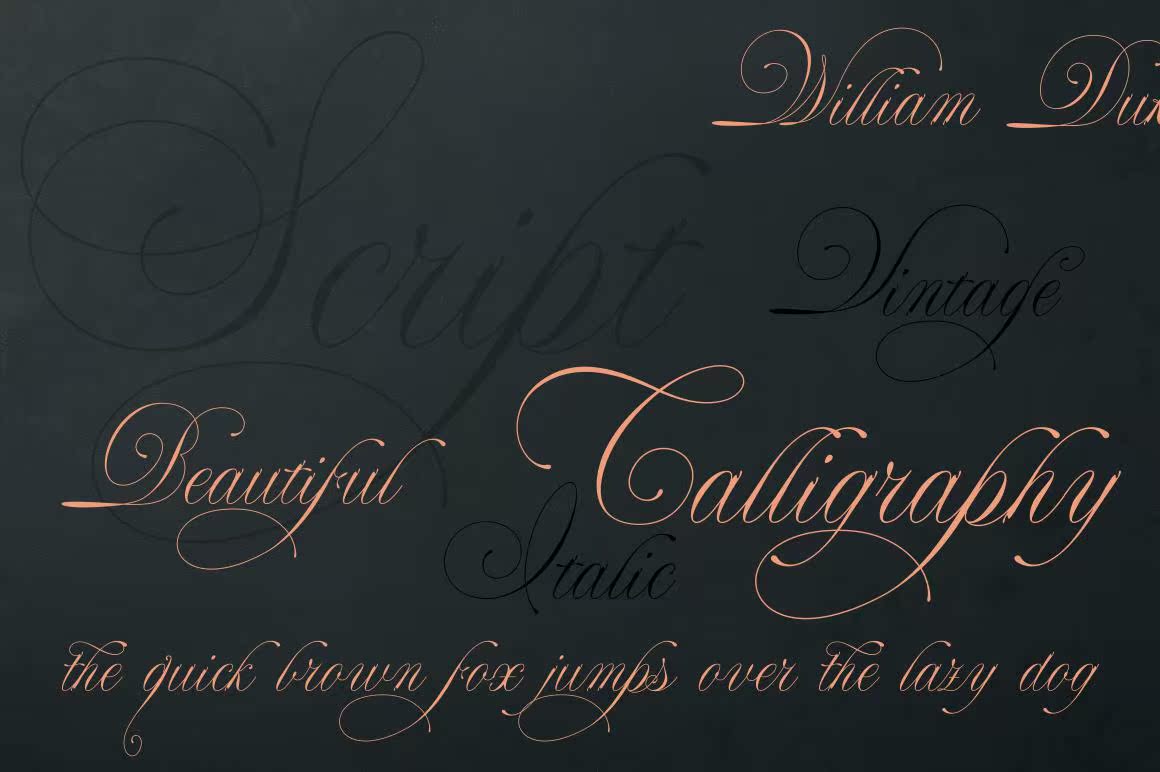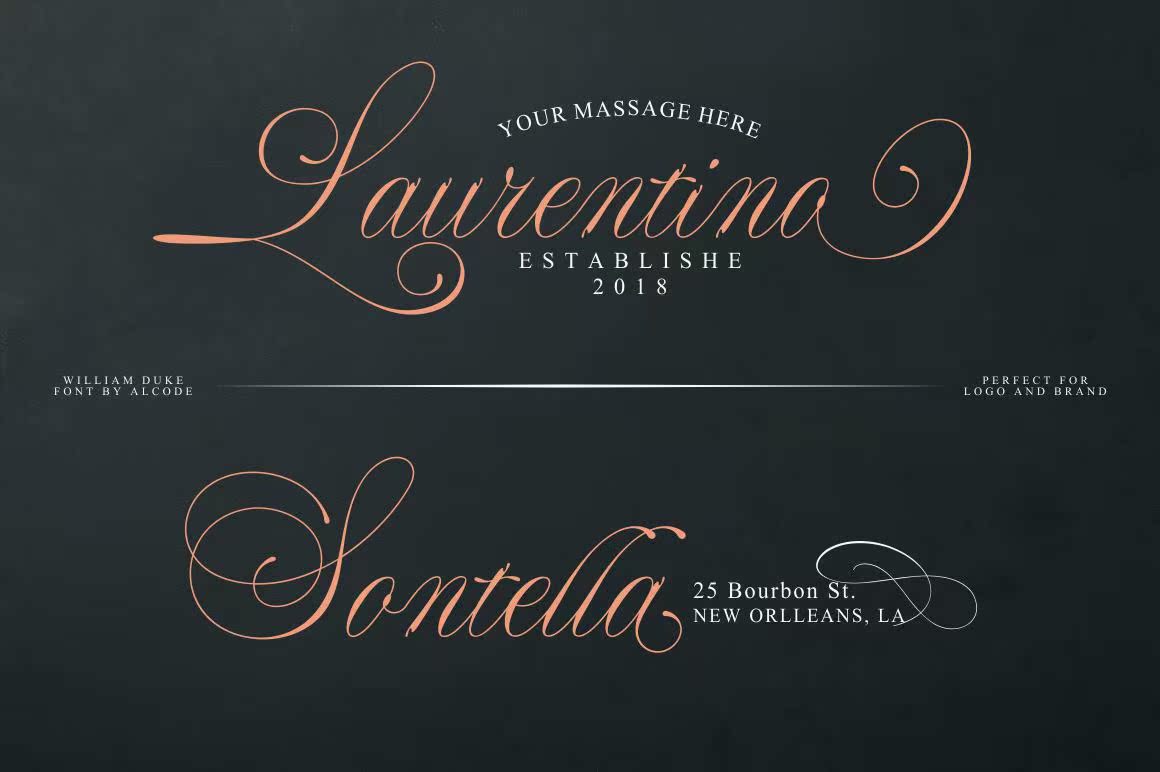
WiliamDukeisaclassicfont.具有开放式打印功能,它可以消除19世纪英国人的手写感觉。因此,它非常适合于婚礼媒体、书皮、贺卡、徽标、品牌、名片和证书,实际上适用于任何需要分类、颜色豪华的设计工作。WiliamDukeisaclassicfont.具有开放式打印功能,它消除了十九世纪英国人的手写感觉。因此,它非常适合于婚礼媒体、书皮、贺卡、徽标、品牌、名片和证书,实际上适用于任何需要分类的设计工作。